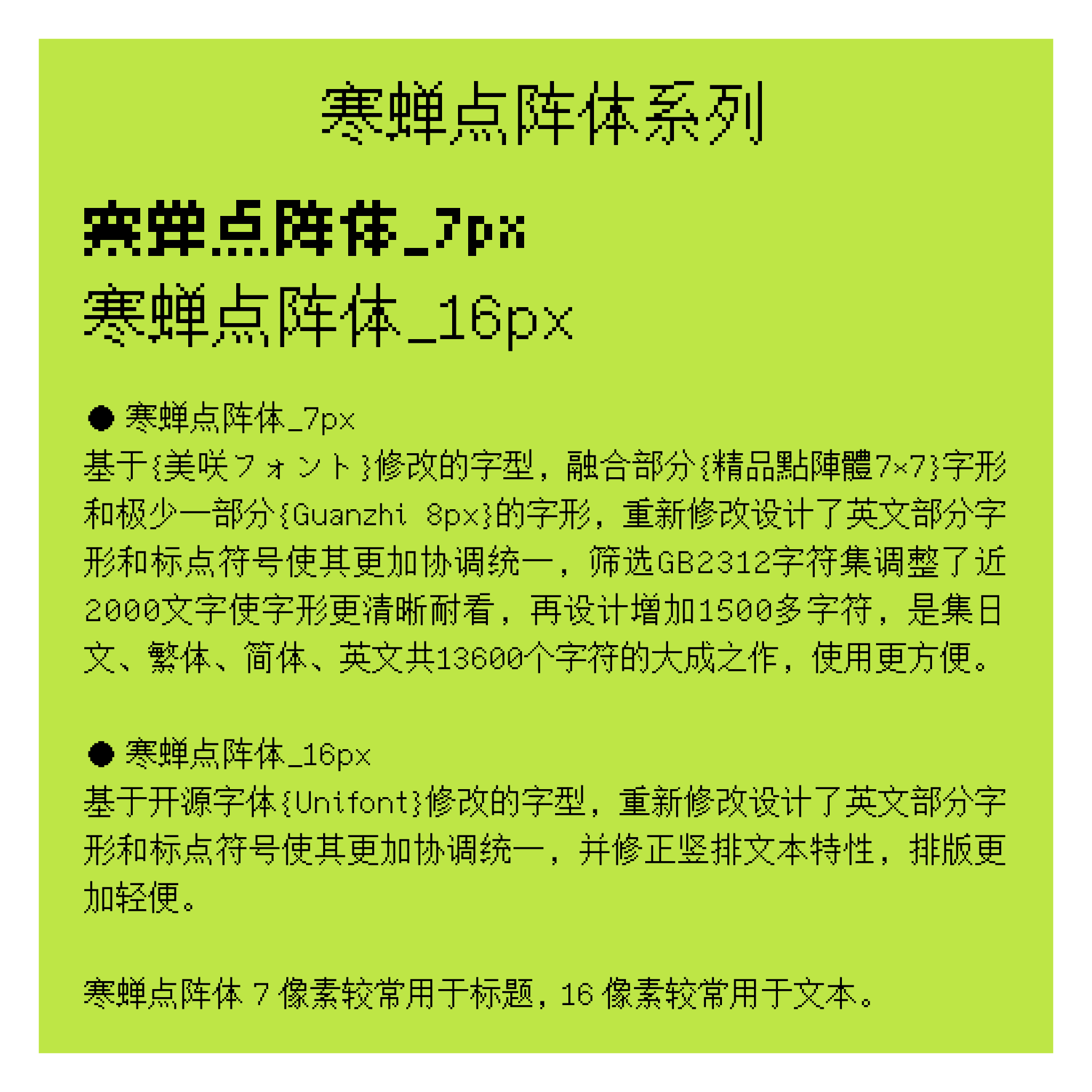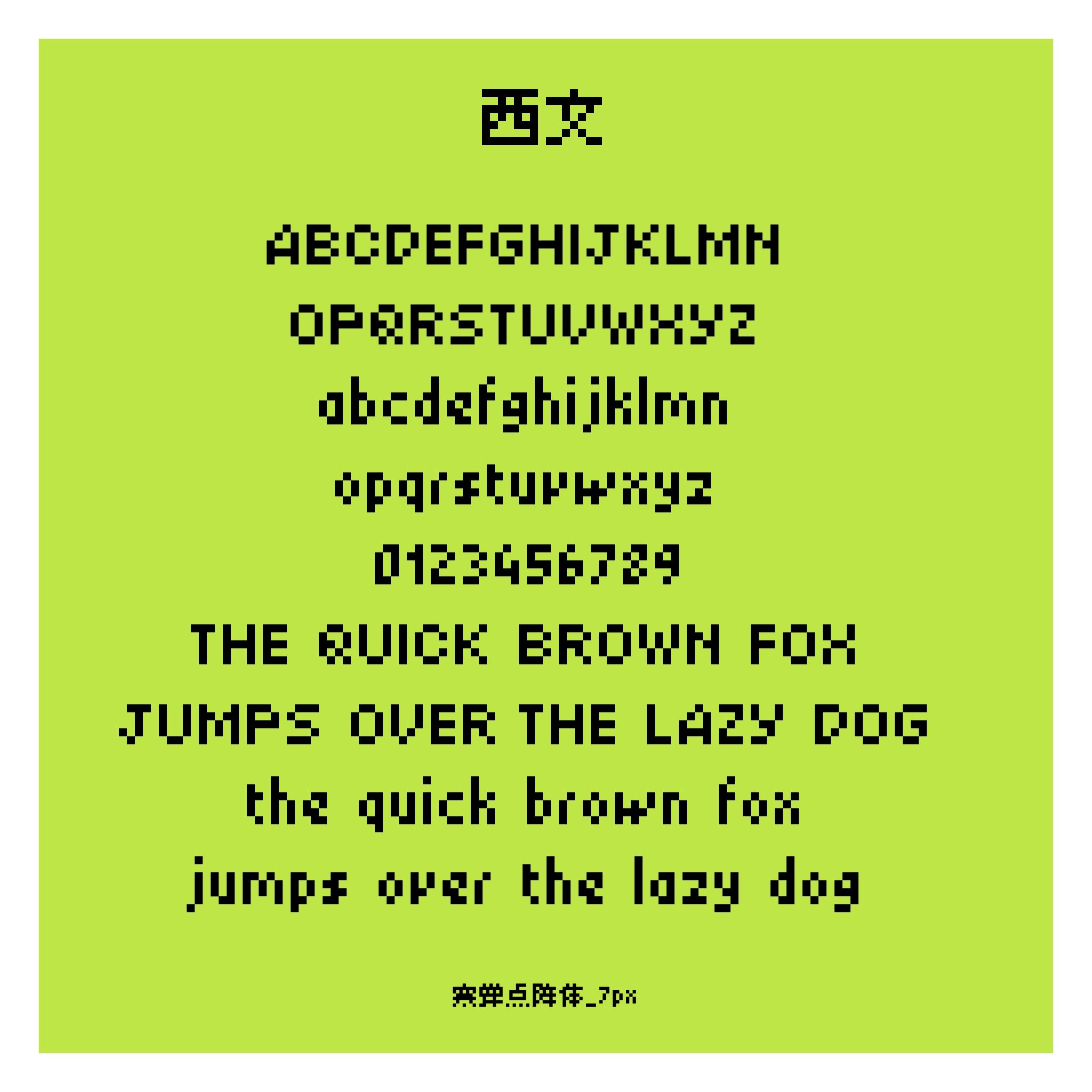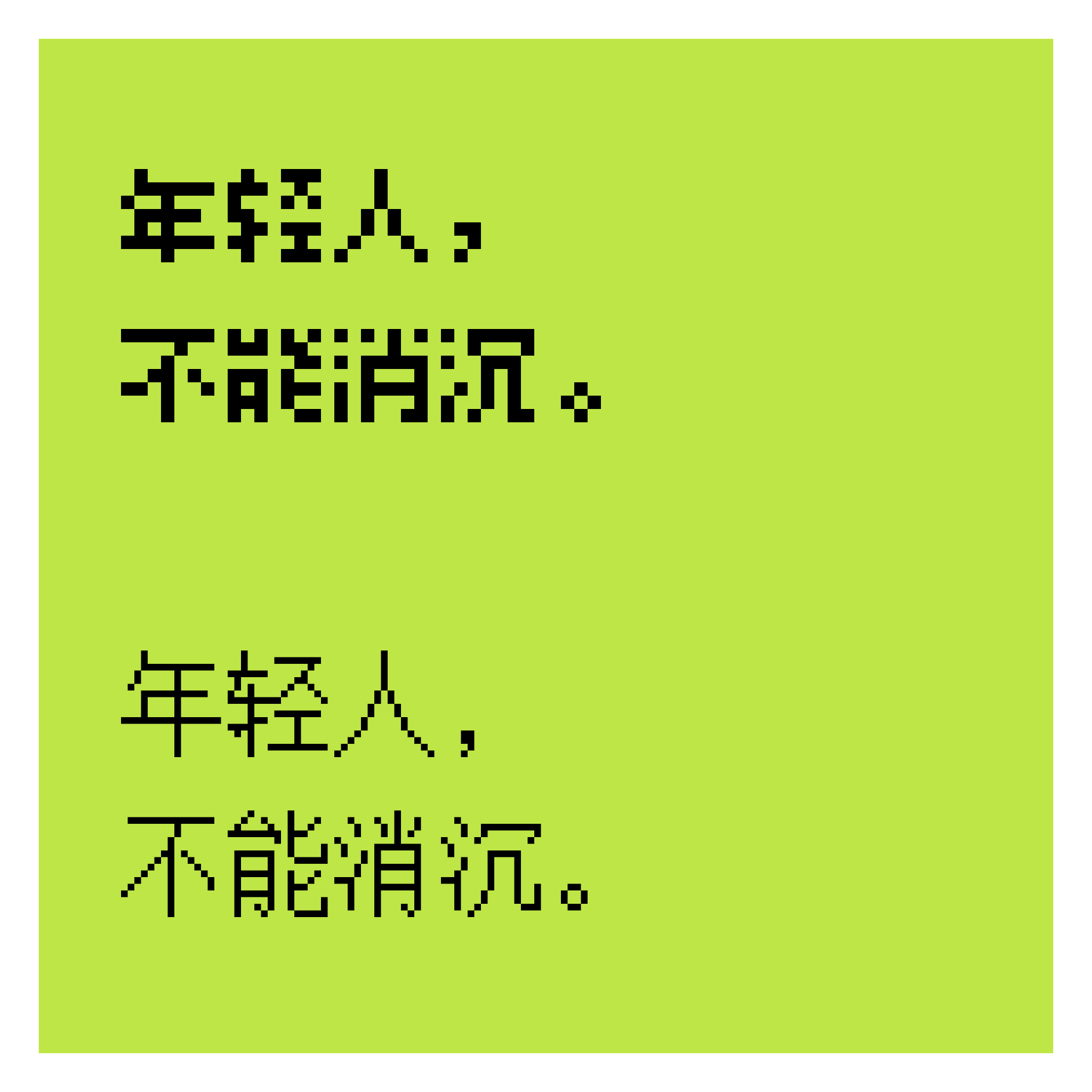
寒蝉点阵体_7px
该字体以广受好评的{美咲フォント}为基础进行深度修改与再创作,精心融合了部分来自{精品點陣體7×7}的独特笔形结构,以及极少一部分取自{Guanzhi 8px}的字形特征。在此融合基础上,设计者对英文部分的所有字母、数字以及各类标点符号进行了全面的重新绘制与优化,力求使其在风格上与中文字符保持高度的协调与视觉统一感。
为提升字体的整体可读性与美观度,设计过程对GB2312标准字符集内的全部汉字进行了细致的筛选与校对,并针对其中近2000个常用或易出错的字形进行了精心的调整与重塑,使其在显示与印刷时都能呈现得更为清晰、结构更匀称耐看。此外,还额外设计并增补了超过1500个新的字符与符号,极大地丰富了字体的覆盖范围。
最终,这一字体项目完成了一项集大成的工作:它不仅完整涵盖了简体中文、繁体中文以及英文字符,更同步支持了完整的日文书写系统,总计包含约13600个精心设计的字符。这一庞大的字符集使得该字体在实际应用中表现出极高的通用性与便利性,无论是日常文档编辑、界面显示,还是创意设计,都能提供出色而连贯的视觉体验。